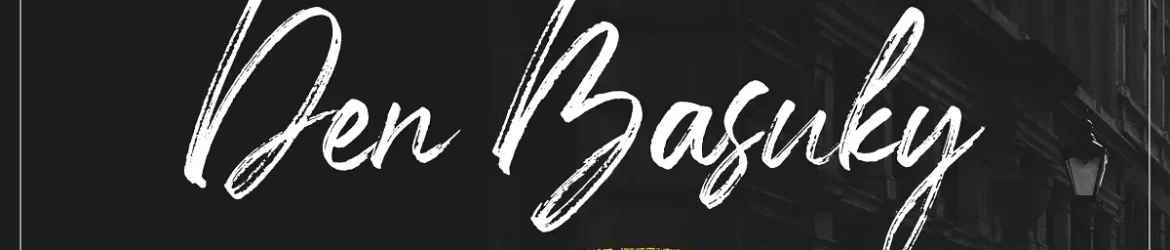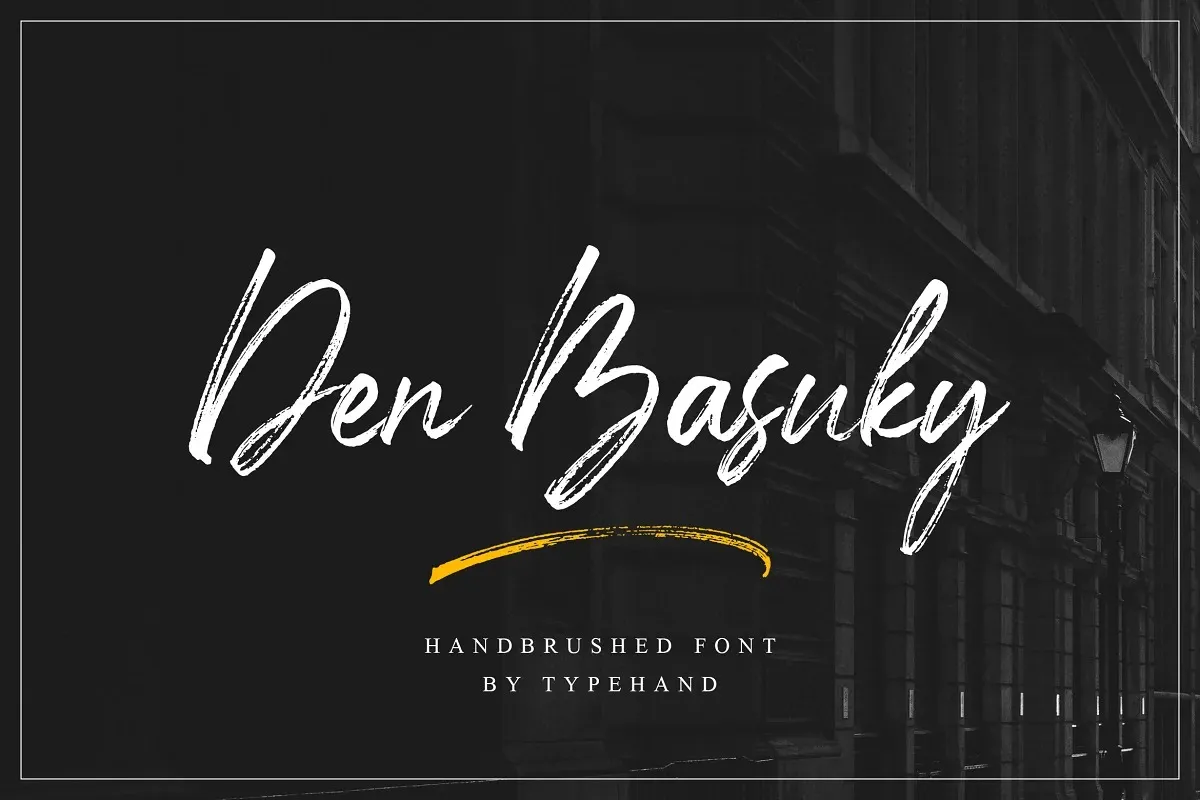
Den Basuky Font – Fonte Grátis
Den Basuky Font
Esta fonte script foi criada pela Typehand Studio e apresenta uma mistura moderna de traços afiados com sentimentos autênticos e descontraídos. Ela inclui swashes, que permitem criar um ar atraente e único em seu design. Ideal para o uso em materiais gráficos pessoais ou corporativos, ela oferece uma personalidade única para qualquer projeto de design. A Den Basuky Font é perfeita para aqueles buscando adicionar profundidade a seus designs com sua textura suave mas atemporal. Com seu estilo casual e moderno, essa fonte atingirá certamente um público desejado em uma variedade de aplicações gráficas.